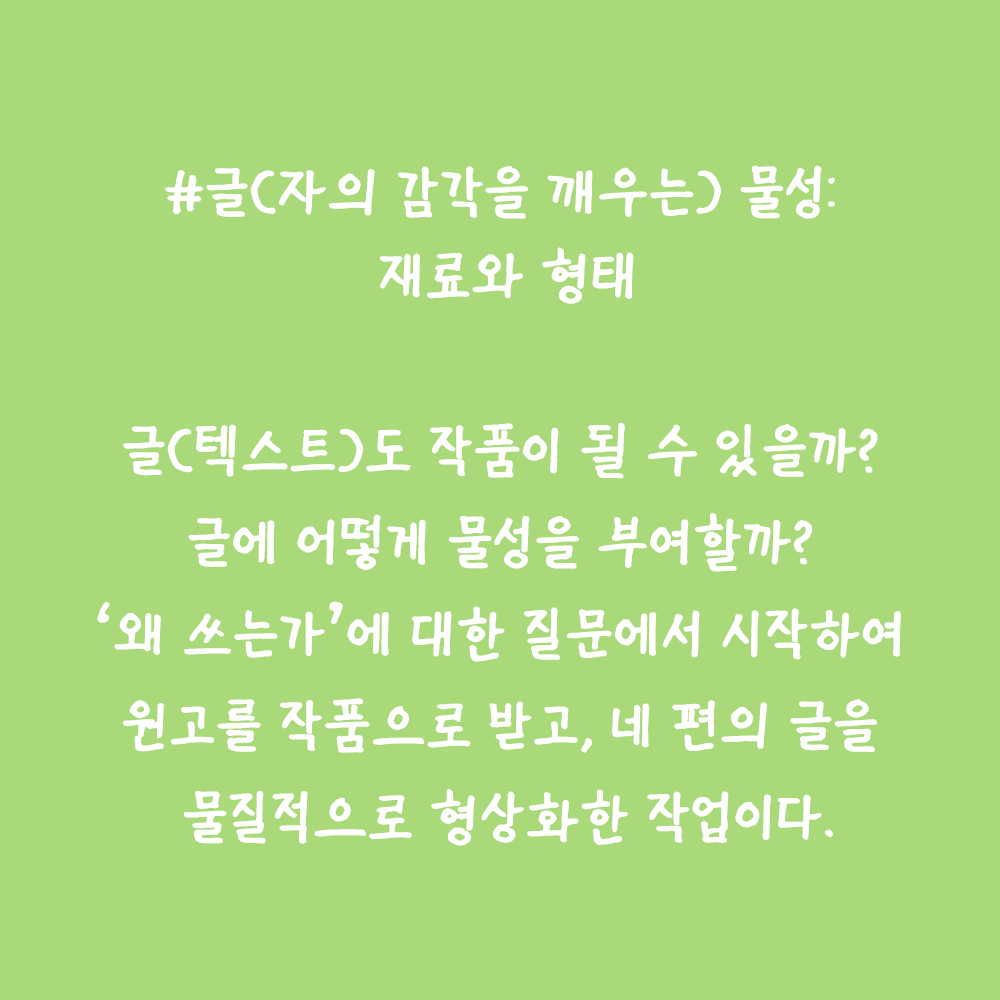
그리운X국한박 빵심
GriunXHangeul Bbangsim
그리운X국한박 빵심 소개
제5회 한글실험프로젝트 《글(자)감(각): 쓰기와 도구》 The 5th Hangeul Design Project 《Senses of Writing: Tools & Perception》 전시기간: 2025.11.19.~2026.3.22. 전시장소: 문화역서울284 RTO 주최·주관: 국립한글박물관 이 손글씨 폰트는 국립한글박물관 제5회 한글실험프로젝트 《글(자)감(각): 쓰기와 도구》 전시 연계 이벤트를 통해 제작되었습니다. 손의 움직임과 쓰는 감각을 그대로 담아, 쓰기의 경험을 폰트로 확장합니다.